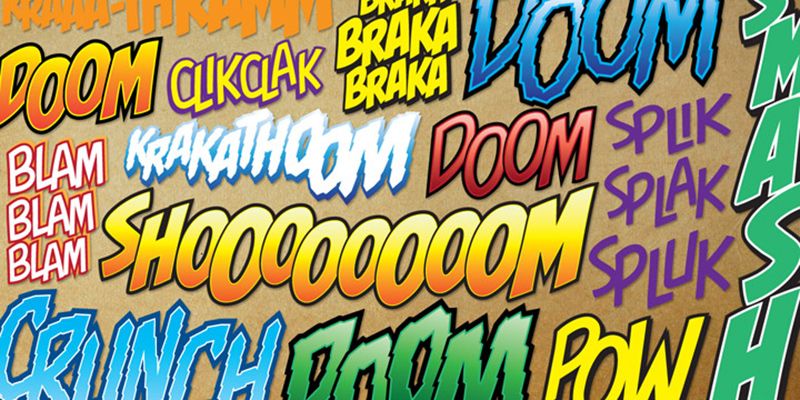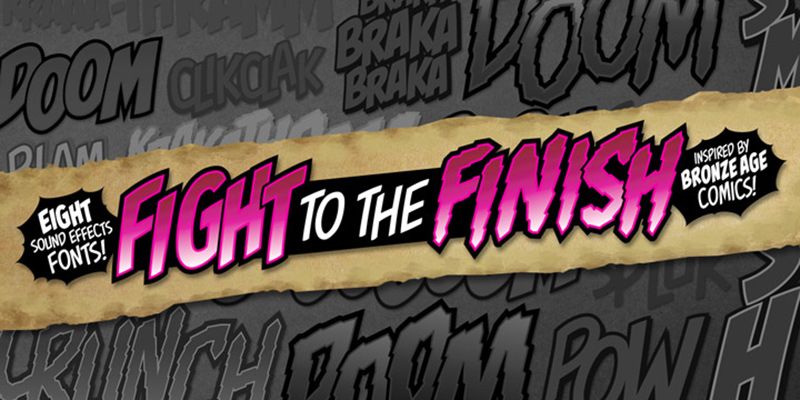
Blambot, fonderie du typographe Nate Piekos, est spécialisée dans les polices de caractères que l’on retrouve dans les bandes dessinées au format papier ou en ligne. Blambot a déjà proposé ses services de lettrage et de design à quasiment toutes les plus grandes maisons d’édition, notamment Marvel Comics, DC Comics, Dark Horse Comics, Image Comics ou encore Oni Press. Les créations de Blambot ont été vendues aussi bien pour des jeux vidéo que des films, des publicités et des emballages de produits, à des entreprises telles que Microsoft, les parcs d’attraction Six Flags, Charles Schulz & Associates, New Yorker Magazine, The Gap, Penguin Random House et Sony.